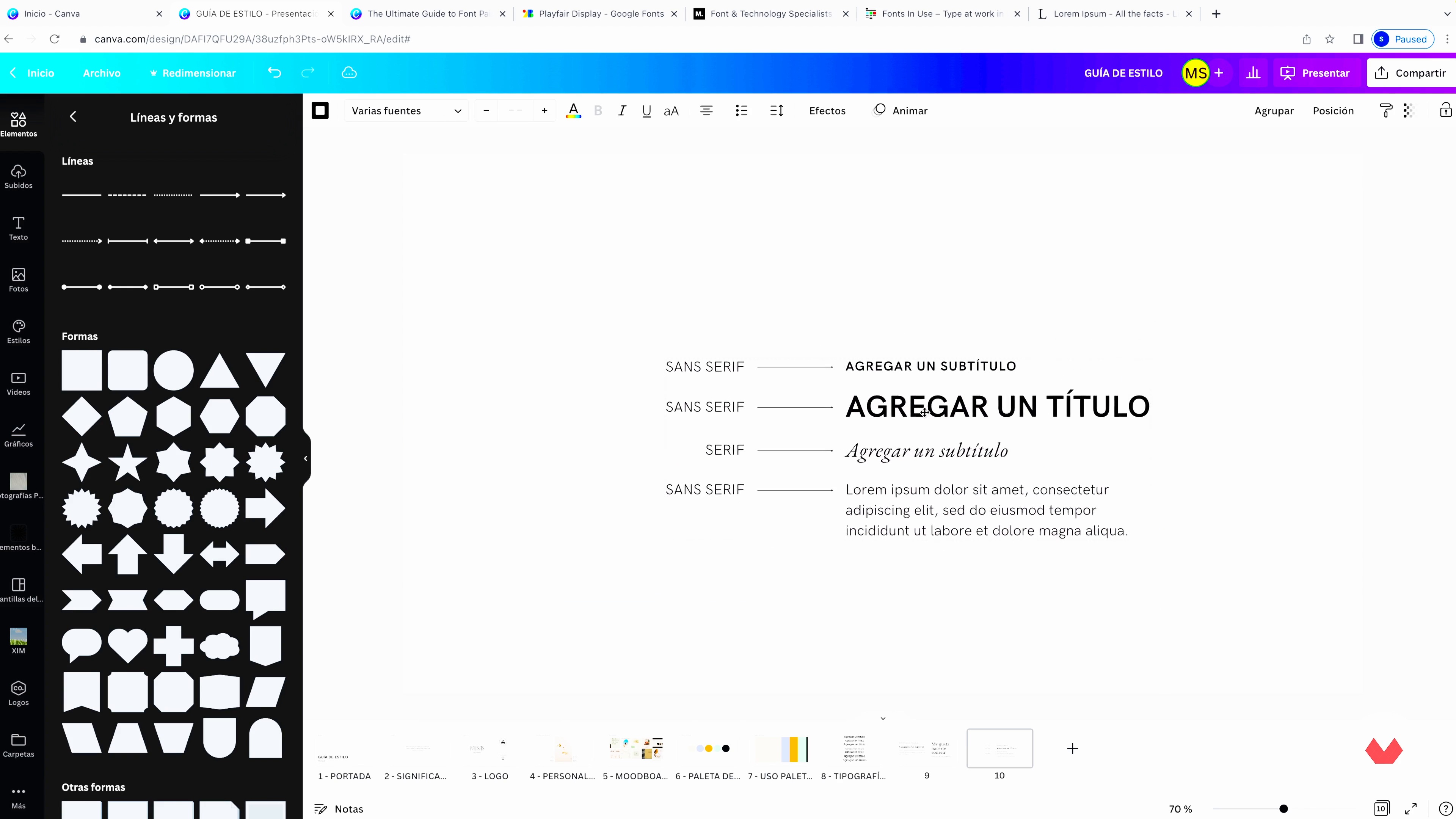
Schriftarten
Über die Videolektion: Schriftarten
“Typografie spielt eine sehr wichtige Rolle, da sie immer lesbar sein muss. In dieser Lektion werde ich einige Tipps zum Kombinieren geben.”
In dieser Videolektion behandelt Daniela Garza das Thema: Schriftarten, das Teil dieses Domestika-Onlinekurses ist: Canva-Präsentationen. Lerne, beeindruckende Präsentationen für deine Marke in Canva zu entwerfen.
“In dieser Lektion zeige ich Ihnen die verschiedenen Schriftarten. Typografie spielt eine sehr wichtige Rolle. da es immer förderfähig sein muss. Ich werde einige Tipps geben, um sie zu kombinieren und ich zeige Ihnen die verschiedenen Klassifizierungen. Mal sehen. Wie wir bereits erwähnt haben, spielt Typografie eine superwichtige Rolle bei der Gestaltung der Präsentation, da es davon abhängt, ob es lesbar ist oder nicht und ob ob Ihre Nachricht verstanden wird oder nicht. Es gibt verschiedene Schriftarten, das sind die wichtigsten. Die erste ist Serif, und das bedeutet, dass es Serifen hat...”